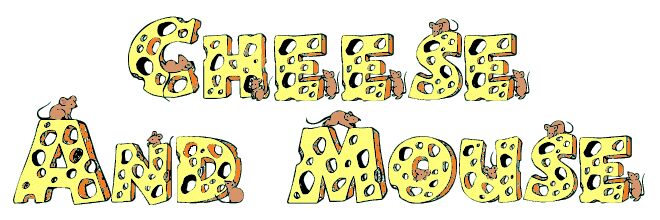
Cheese and Mouse di Melle Derieppe Claude è un font display gratuito in stile cartoon che trasforma ogni parola in una fetta di formaggio coi buchi, completa di piccoli topolini curiosi che si arrampicano sulle lettere. Le forme corpose e irregolari e le linee tratteggiate evocano un aspetto disegnato a mano e giocoso, come in un fumetto della domenica mattina o in un disegno su un menu per bambini. I contorni in bianco e nero invitano ad aggiungere colore, consistenza e ombreggiature, così puoi calibrare il livello di simpatia in base al tuo progetto.
Con Cheese and Mouse, i tuoi titoli risulteranno subito divertenti, amichevoli e un po' birichini: perfetto per copertine di libri per bambini, inviti di compleanno, insegne di food truck, branding per negozi di formaggi, poster scolastici, striscioni per feste e miniature YouTube per contenuti per bambini. Questo font gratuito dà il meglio di sé in grande formato, quindi lascialo dominare nei titoli e abbinalo a un font sans serif pulito per il corpo del testo, mantenendo così la leggibilità e un fascino irresistibile.